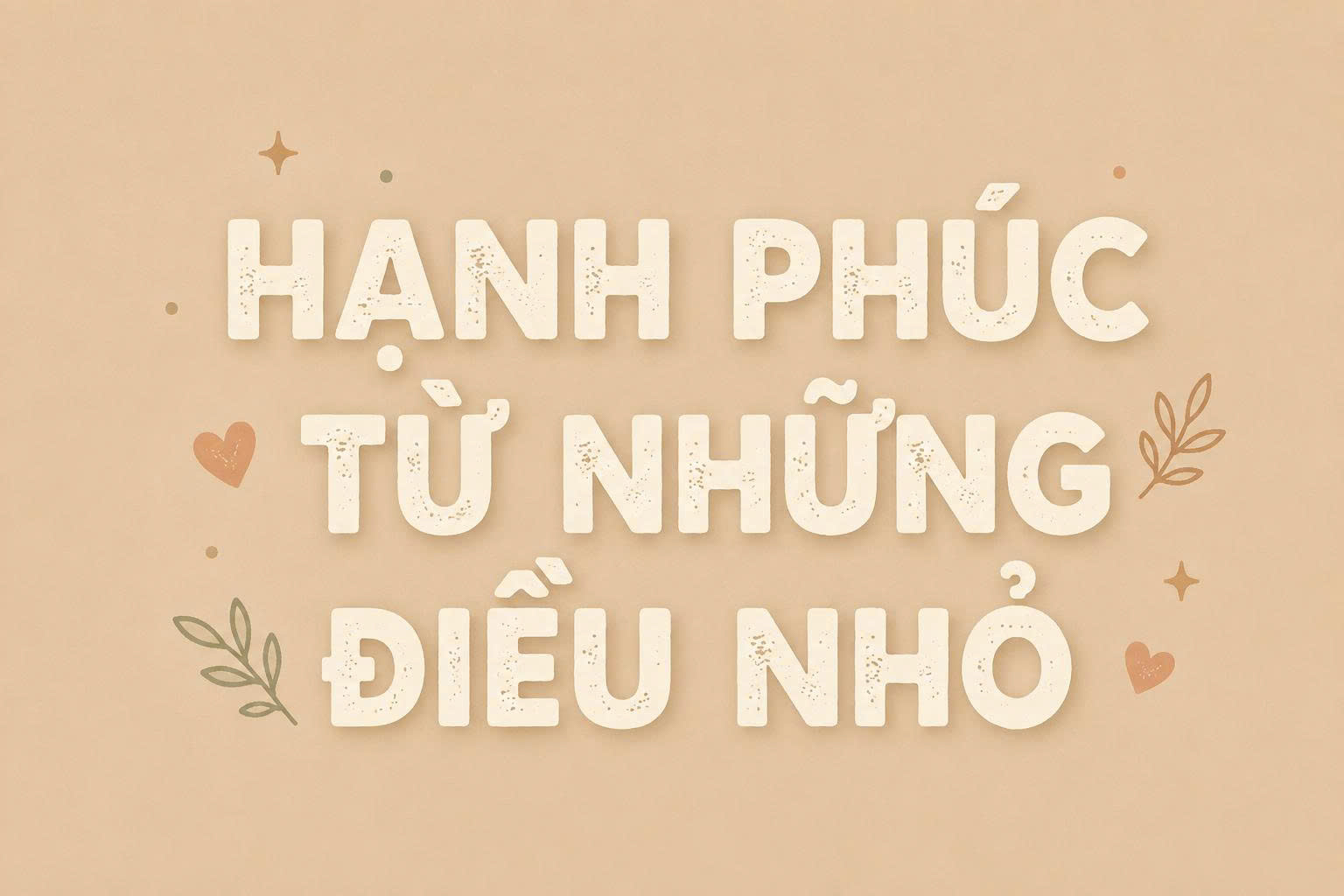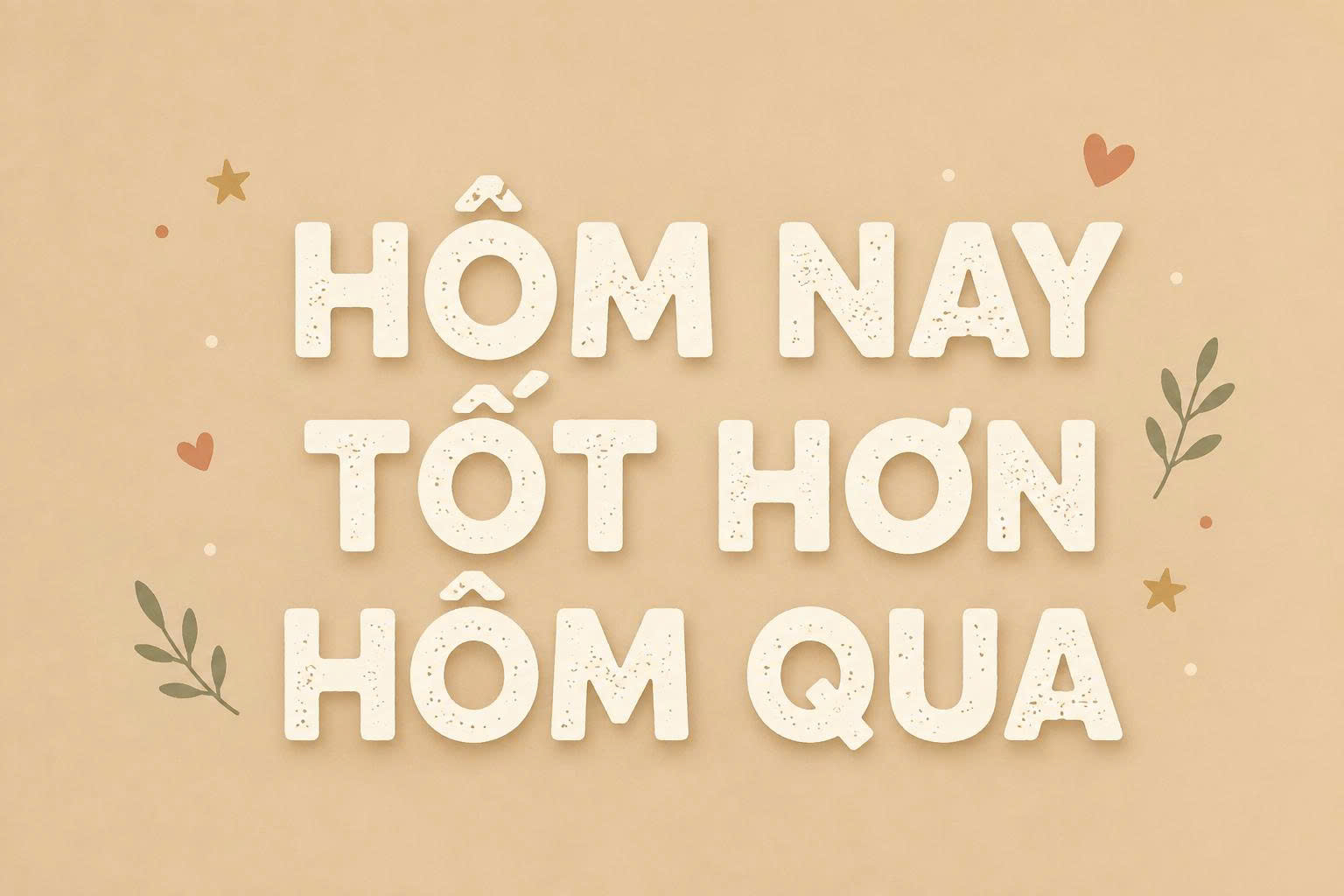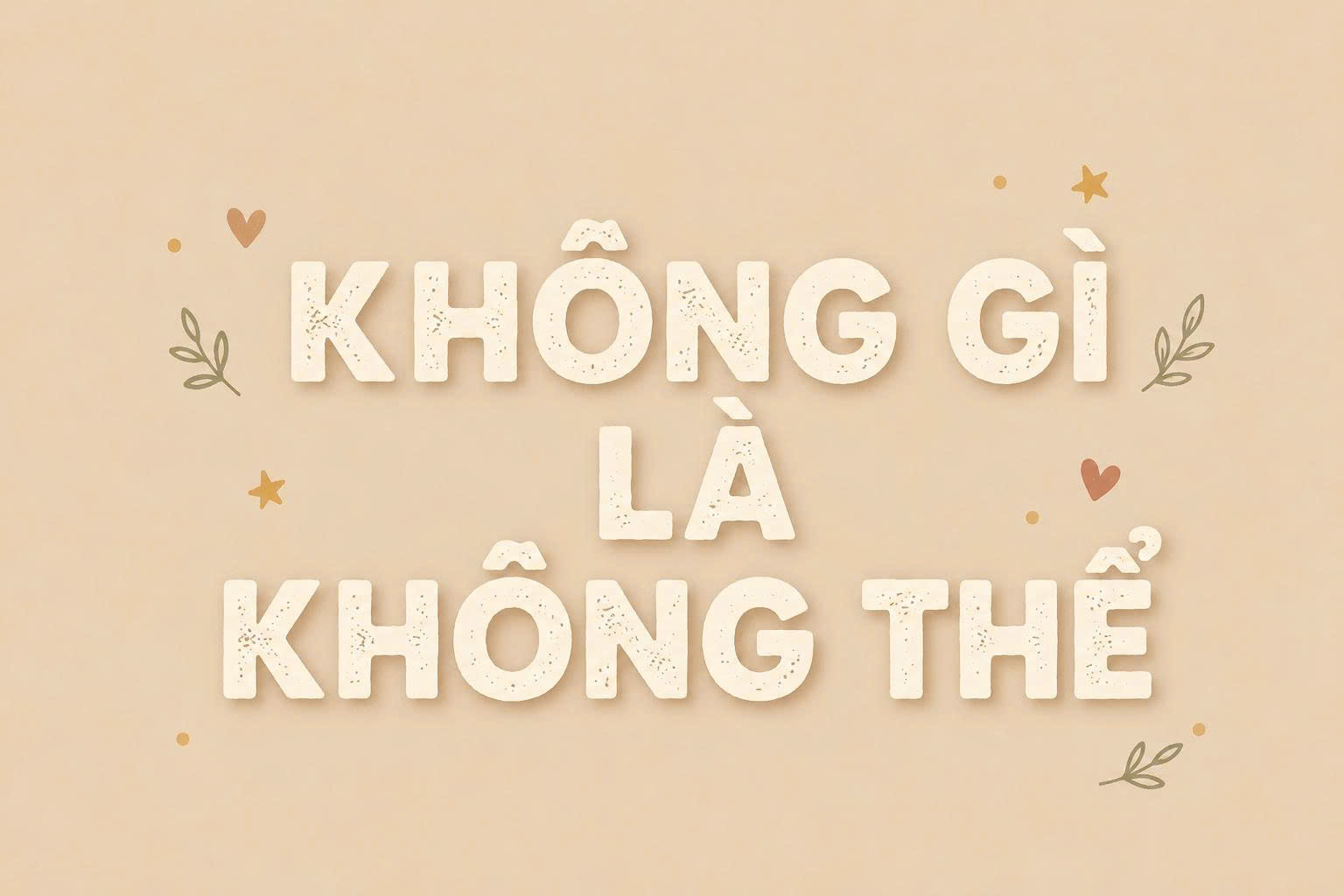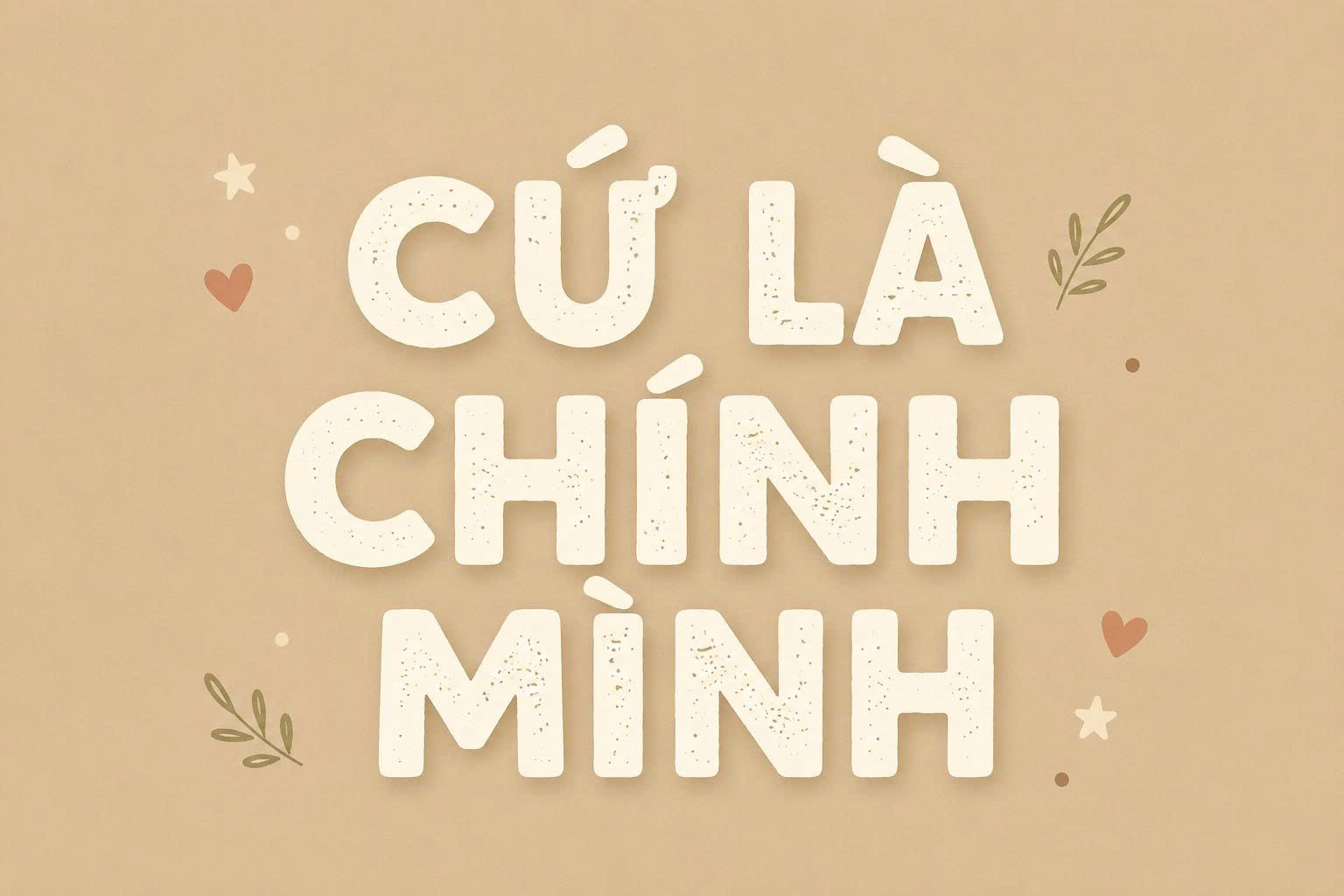
Font Việt hóa SVN A Love Of Thunder là bộ phông chữ thuộc dòng Display với những đường nét dày dặn, mang đậm phong cách Retro và Vintage của thập niên 70. Với cấu trúc chữ mạnh mẽ, các góc bo tròn tinh tế cùng sự biến tấu độc đáo ở các ký tự đặc biệt, đây là lựa chọn hàng đầu cho những dự án thiết kế cần tạo dấu ấn hoài cổ nhưng vẫn hiện đại. Doozypack.vn chia sẻ link tải font SVN A Love Of Thunder Việt hóa chuẩn, hỗ trợ đầy đủ bảng mã tiếng Việt để bạn tự do sáng tạo mà không lo lỗi hiển thị dấu thanh.
Đặc điểm thẩm mỹ của font SVN A Love Of Thunder Việt hóa
SVN A Love Of Thunder không chỉ đơn thuần là một bộ font chữ đậm, nó là một tác phẩm nghệ thuật mang hơi thở của thời đại hoàng kim đồ họa thế kỷ trước.
Thiết kế Bold mạnh mẽ với cấu trúc hình học độc đáo
Đặc trưng lớn nhất của SVN A Love Of Thunder là độ dày nét chữ (Font weight) cực kỳ lớn, tạo nên sự vững chãi và thu hút thị giác ngay từ cái nhìn đầu tiên. Các chữ cái được thiết kế với cấu trúc hình học cân đối, kết hợp giữa những đường thẳng dứt khoát và các đường cong mềm mại ở những điểm nối. Phong cách này gợi nhắc đến các poster phim hoặc bìa album nhạc cũ, mang lại cảm giác hoài niệm đầy cá tính cho bản thiết kế.
Khả năng hiển thị tiếng Việt chỉn chu, không lỗi dấu
Nhiều designer thường gặp khó khăn khi sử dụng các font Display nước ngoài vì hệ thống dấu tiếng Việt thường bị nhảy font hoặc sai lệch vị trí. Tuy nhiên, phiên bản font SVN-A Love Of Thunder Việt hóa đã được đội ngũ Style Việt hóa tinh chỉnh kỹ lưỡng. Các dấu thanh (sắc, huyền, hỏi, ngã, nặng) được đặt ở vị trí cân đối, hài hòa với độ dày của nét chữ gốc, đảm bảo tính thẩm mỹ cao nhất cho các ấn phẩm in ấn chuyên nghiệp.
03 Ứng dụng của font SVN A Love Of Thunder trong thiết kế bao bì & Branding
Tại Doozypack.vn, chúng tôi thấy rằng SVN A Love Of Thunder cực kỳ hiệu quả khi được ứng dụng vào các dòng sản phẩm mang phong cách “Classic”:
- Bao bì cà phê và trà: Nét chữ dày mang lại cảm giác mộc mạc, đậm đà, rất hợp khi in trên chất liệu túi giấy Kraft nâu.
- Thiết kế Logo & Header: Với tính nhận diện cực mạnh, font chữ này thường được chọn làm tiêu đề chính cho website hoặc làm tên thương hiệu cho các quán cà phê, tiệm bánh phong cách Retro.
- Hộp giấy quà tặng: Khi kết hợp với những họa tiết Vintage, font chữ này giúp nâng tầm giá trị của hộp sản phẩm, khiến khách hàng có cảm giác đây là một thương hiệu lâu đời và uy tín.
03 Những lưu ý kỹ thuật khi in ấn với dòng font Display dày như SVN A Love Of Thunder
Việc in một phông chữ có độ phủ mực lớn như SVN A Love Of Thunder đòi hỏi sự hiểu biết về kỹ thuật sản xuất để tránh thành phẩm bị lỗi:
- Kiểm soát độ tràn mực (Dot Gain): Do nét chữ vốn đã dày, khi in trên các loại giấy có độ thấm hút mực cao như giấy Kraft hoặc giấy Ivory không cán màng, mực có thể bị lan nhẹ. Bạn nên giãn khoảng cách chữ (Kerning) rộng hơn một chút để tránh việc các ký tự bị bết vào nhau sau khi in.
- Phối màu sắc Retro: Để làm nổi bật nét hoài cổ, bạn nên chọn các tông màu trầm như nâu đất, xanh rêu, vàng mù tạt hoặc cam cháy. Tránh các màu quá rực rỡ nếu muốn giữ đúng tinh thần của bộ font.
2. Font này có phù hợp để in văn bản dài (Body text) không?
Không nên. Với độ dày nét cực lớn, font chữ này chỉ nên dùng cho tiêu đề (Heading) từ 1-5 từ. Nếu dùng cho đoạn văn dài sẽ gây rối mắt và rất khó đọc.